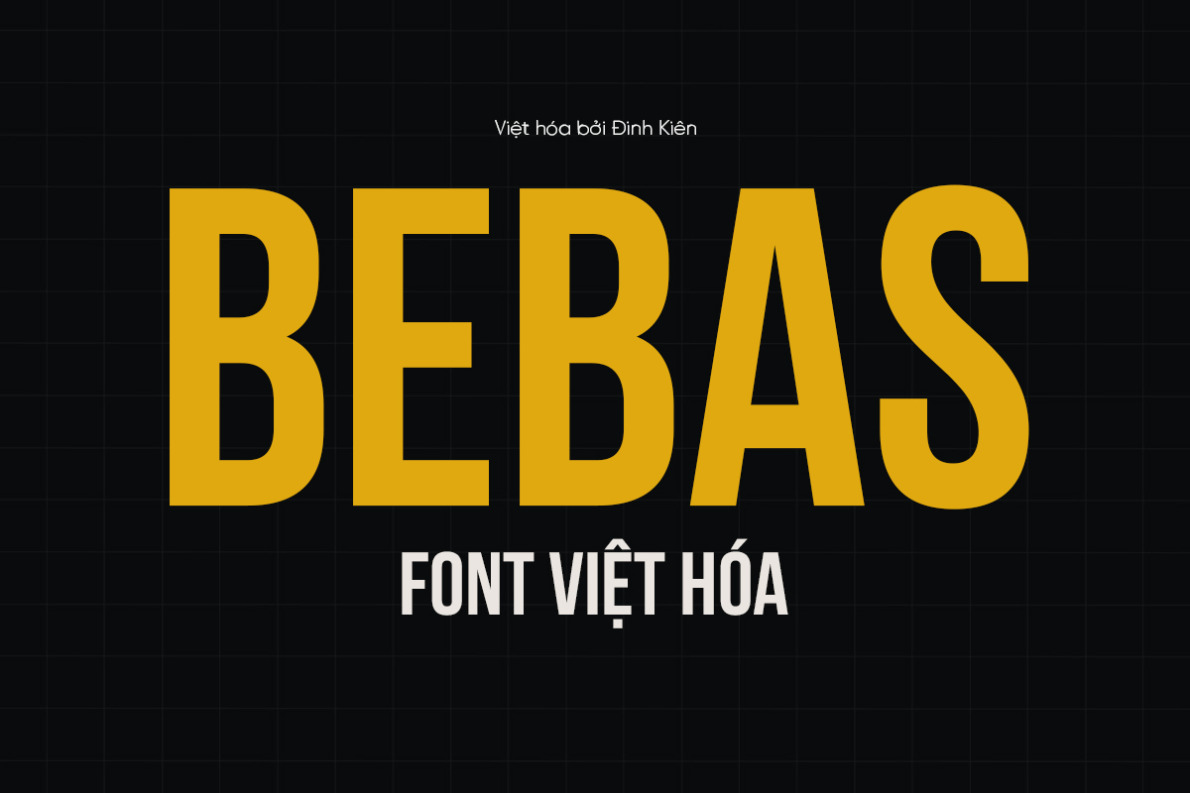
Font Việt hóa UTM Bebas | Link tải
Font Việt hóa UTM Bebas là một font chữ nằm trong bộ font UTM. UTM Font là viết tắt của bộ Unicode Thiên Minh do anh Đinh Kiên việt hóa.